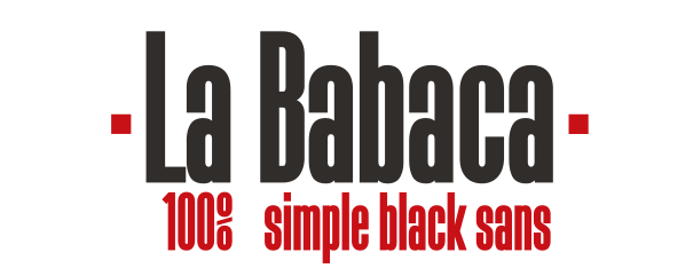
La Babaca Font
La Babaca es una tipografía black, sin serif y comprimida de formas geométricas muy simples, sin adornos, una fuente display sobria, que proporciona un gran ahorro de espacio para títulos grandes.
The babaca is a black typeface without serifs and compressed very simple geometric shapes, unadorned sober display font that provides a great space saver for big titles.
• Letras griegas
• Letras alternativas
• Greek characters
• Alternative characters